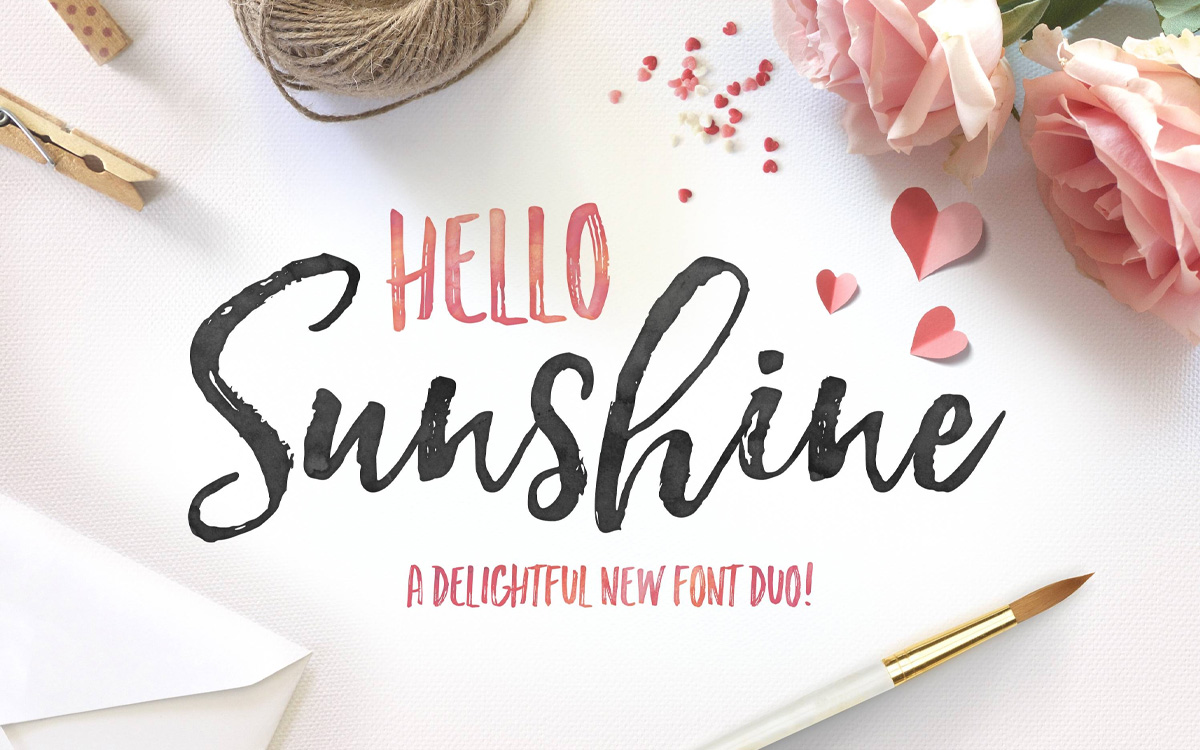
Tấm thiệp cưới không chỉ là lời mời trân trọng gửi đến quan khách mà còn là tác phẩm nghệ thuật đại diện cho câu chuyện tình yêu lãng mạn của đôi lứa. Trong nghệ thuật thiết kế thiệp cưới hiện đại, bộ font chữ viết tay, chữ ký mềm mại SVN-Hello Sunshine nổi lên như một sự lựa chọn hoàn hảo, mang đến vẻ đẹp ngọt ngào, tinh tế và đầy cảm xúc. Với nét chữ bay bổng tự nhiên cùng khả năng Việt hóa chỉn chu, phông chữ này hứa hẹn sẽ nâng tầm mọi ấn phẩm ngày cưới của bạn.
Font Chữ Viết Tay, Chữ Ký Mềm Mại Cho Thiệp Cưới, Đám Cưới SVN-Hello Sunshine – Lựa Chọn Hoàn Hảo Cho Ngày Trọng Đại
Trong thiết kế đồ họa sự kiện và đám cưới, phông chữ (typography) đóng vai trò linh hồn, truyền tải cảm xúc và định hình phong cách chủ đạo cho toàn bộ không gian buổi lễ. Bộ font chữ SVN-Hello Sunshine được thiết kế dựa trên nguồn cảm hứng từ những nét chữ ký cá nhân phóng khoáng, kết hợp cùng kỹ thuật calligraphy hiện đại để tạo nên từng đường nét uốn lượn vô cùng tự nhiên và mềm mại.
Sự xuất hiện của SVN-Hello Sunshine giúp các nhà thiết kế thiệp cưới, các cặp đôi tự thiết kế ấn phẩm ngày trọng đại dễ dàng tạo nên dấu ấn cá nhân đậm nét. Không còn là những nét chữ in đứng khô khan, bộ phông chữ này mang tới cảm giác chân thật như chính tay chú rể và cô dâu đang cẩn xát từng dòng chữ nắn nót gửi đến người thân, bạn bè. Đây chính là mảnh ghép còn thiếu cho những bộ sưu tập thiệp cưới phong cách Vintage, Rustic, Modern Elegant hay Fine Art.
1. Đường Nét Viết Tay Uyển Chuyển, Tự Nhiên Và Nữ Tính
Điểm đặc trưng nổi bật nhất của SVN-Hello Sunshine chính là cấu trúc nét chữ được tạo hình khéo léo, mô phỏng chân thực nét bút mực chảy trên nền giấy cao cấp. Các đường nét cao thấp bất quy tắc một cách nghệ thuật (baseline variation) tạo nên nhịp điệu thị giác sinh động, khiến câu chữ trở nên mềm mại, ngọt ngào và tràn đầy sức sống. Mỗi chữ cái đều có độ nảy và độ lượn hoàn hảo, giúp câu từ không bị gượng gạo hay cứng nhắc như các phông chữ máy tính thông thường.
2. Bộ Ký Tự Tiếng Việt Được Việt Hóa Chuẩn Xác Và Tối Ưu Tỉ Lệ
Một trong những nỗi lo lớn nhất của các designer khi chọn font chữ ký hay font script nước ngoài là thiếu dấu tiếng Việt hoặc dấu bị đè, mất thẩm mỹ. Bản Việt hóa SVN-Hello Sunshine đã giải quyết triệt để vấn đề này. Hệ thống dấu thanh (sắc, huyền, hỏi, ngã, nặng) và các dấu phụ (nón, râu) được tinh chỉnh thủ công kỹ lưỡng về cả kích thước lẫn khoảng cách. Điều này đảm bảo rằng tên cô dâu chú rể hay các đoạn văn bản tiếng Việt dài vẫn giữ được sự hài hòa, nét đẹp thanh thoát vốn có mà không gặp bất kỳ lỗi hiển thị nào.
3. Tích Hợp Phong Cách Chữ Ký (Signature Style) Với Các Ký Tự Thay Thế (Ligatures & Swashes)
SVN-Hello Sunshine không đơn thuần là một font chữ script thông thường mà còn tích hợp bộ tính năng OpenType phong phú với các ký tự thay thế (Alternate Characters), nét gạch chân trang trí (Swashes) và bộ nối chữ (Ligatures). Tính năng này cho phép bạn tạo ra những bản phối tên cô dâu chú rể mang phong cách “Chữ ký nghệ thuật” độc bản. Các nét móc đầu, nét bay đuôi kéo dài mềm mại giúp điểm xuyết cho tên của hai nhân chính thêm phần nổi bật và sang trọng trên bìa thiệp hay bảng đón khách (Welcome Board).
4. Khả Năng Ứng Dụng Đa Dạng Trên Nhiều Ấn Phẩm Ngày Cưới
Bên cạnh thiệp cưới truyền thống, bộ font chữ viết tay SVN-Hello Sunshine còn cho thấy sự linh hoạt tuyệt vời khi ứng dụng vào hệ thống ấn phẩm cưới đồng bộ (Wedding Stationery Set). Bạn có thể dễ dàng sử dụng font chữ này để thiết kế:
- Thiệp báo hỷ và Thiệp mời chính thức: Dùng cho phần tiêu đề, tên cặp đôi hoặc các câu trích dẫn tình yêu (Love quotes).
- Bảng Welcome cưới và Bảng sơ đồ bàn tiệc (Seating Chart): Tạo nét điểm nhấn nghệ thuật ấn tượng ngay từ lối vào sảnh tiệc.
- Thực đơn tiệc cưới (Menu) và Thẻ tên bàn (Place Card): Mang lại cảm giác chỉn chu, trân trọng đến từng vị khách mời.
- Thiệp cảm ơn (Thank You Card) và Thẻ quà tặng (Favor Tags): Gửi gắm lời tri ân chân thành với nét chữ ấm áp.
- Video cưới và Album ảnh cưới: Làm tựa đề cho các thước phim kỷ niệm hoặc trang trí photo album online.
5. Hiển Thị Sắc Nét Cho In Ấn Chuyên Nghiệp Và Thiết Kế Digital
Font SVN-Hello Sunshine được xây dựng trên nền tảng vector chất lượng cao, các điểm neo (anchor points) được tối ưu hóa mượt mà. Nhờ đó, font chữ đảm bảo chất lượng hiển thị sắc nét dù bạn in ở kích thước cực nhỏ trên thẻ quà tặng hay phóng to hàng mét trên backdrop sân khấu. Ngoài ra, phông chữ này tương thích hoàn hảo với các kỹ thuật in ấn cao cấp hiện nay như in ép kim (Foil Stamping), in dập nổi (Embossing), in UV trên acrylic hoặc in kỹ thuật số trên giấy mỹ thuật có gân.
Mẹo Phối Font SVN-Hello Sunshine Trong Thiết Kế Thiệp Cưới Chuyên Nghiệp
Để bài thiết kế thiệp cưới đạt hiệu quả thẩm mỹ cao nhất, việc kết hợp phông chữ (Font Pairing) là vô cùng quan trọng. Do SVN-Hello Sunshine sở hữu nét chữ viết tay mềm mại và có tính trang trí cao, bạn nên áp dụng các quy tắc phối font sau:
- Kết hợp với Font Serif cổ điển: Sử dụng SVN-Hello Sunshine cho tên cô dâu chú rể, kết hợp cùng một font chữ có chân (Serif) nhẹ nhàng cho các thông tin ngày giờ, địa điểm để tạo sự cân bằng và dễ đọc.